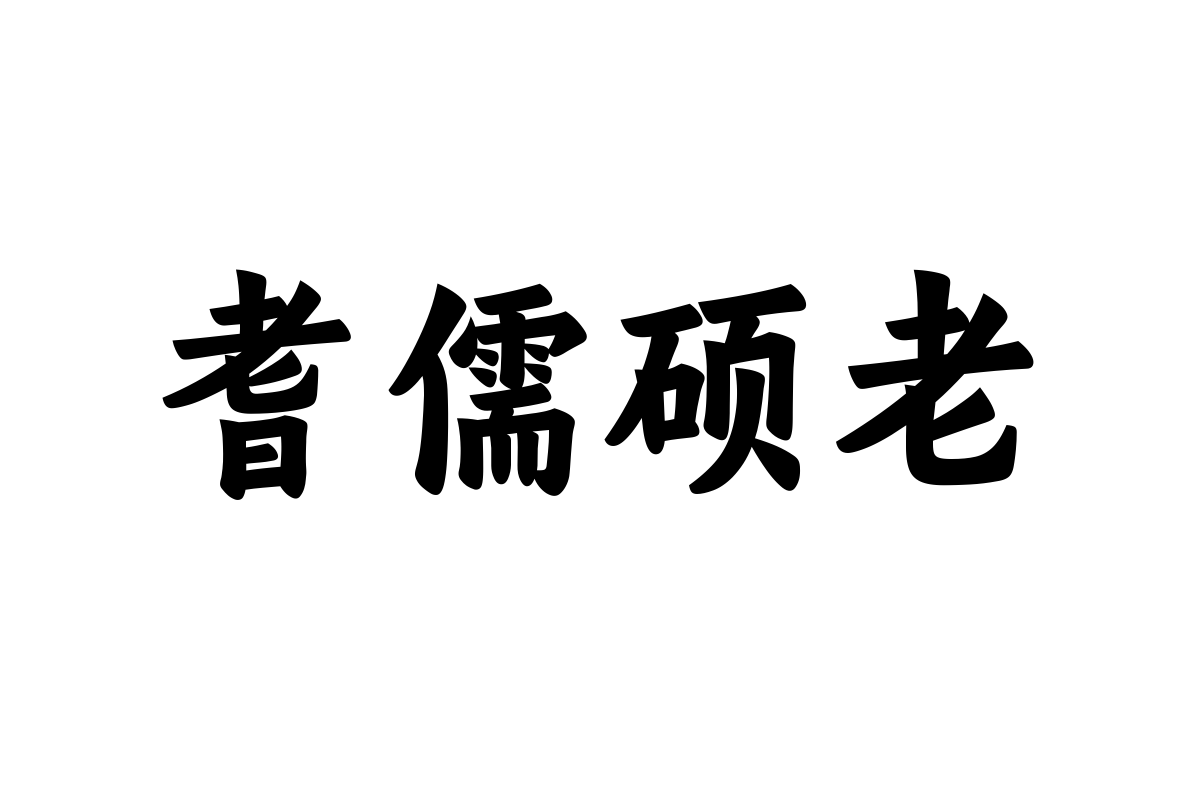
汉仪楷95是一款非常受欢迎的中文字体,它的特点是字形规整、结构清晰、笔画流畅。这款字体适用于各种需要书写中文的场合,如报纸、杂志、广告、书籍等。它的设计灵感来源于传统的楷书,但又不失现代感,使得它在保持传统韵味的同时,又具有很高的辨识度和美感。
汉仪楷95的特点如下:
1. 字形规整:这款字体的字形结构严谨,每个字都有明确的边界,笔画粗细适中,易于阅读。
2. 结构清晰:汉仪楷95的每个字都有一定的空间布局,使得整个字体看起来既紧凑又不失灵动。
3. 笔画流畅:汉仪楷95的笔画流畅自然,没有生硬的感觉,给人一种优雅的感觉。
4. 易识别:由于其独特的字形结构和清晰的边界,汉仪楷95在各种场合下都能被轻易识别。
5. 适用广泛:无论是在印刷品还是电子媒体上,汉仪楷95都能展现出其独特的魅力。
总的来说,汉仪楷95是一款非常适合用于各种中文书写场合的字体,无论是用于正式的文件还是用于创意的设计,它都能为你的作品增添一份独特的美感。